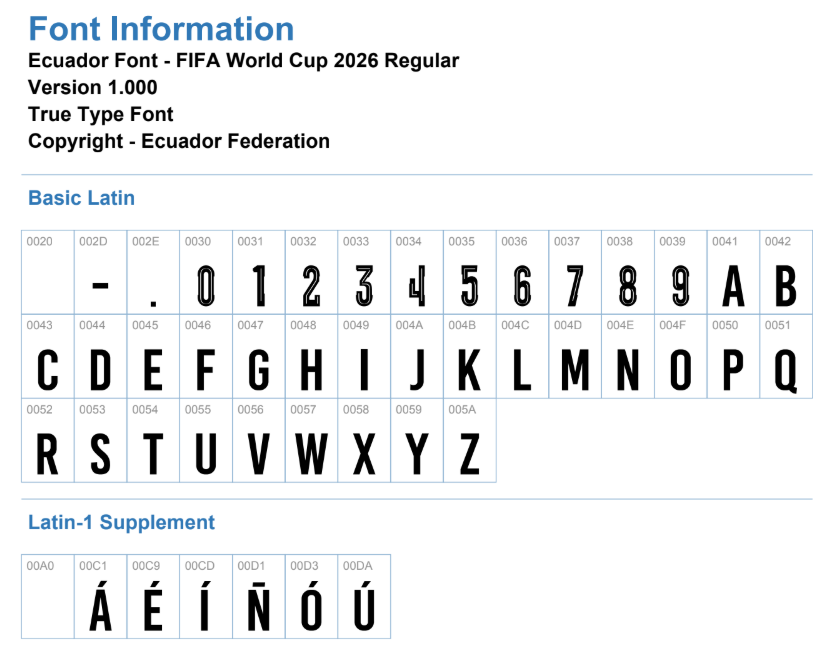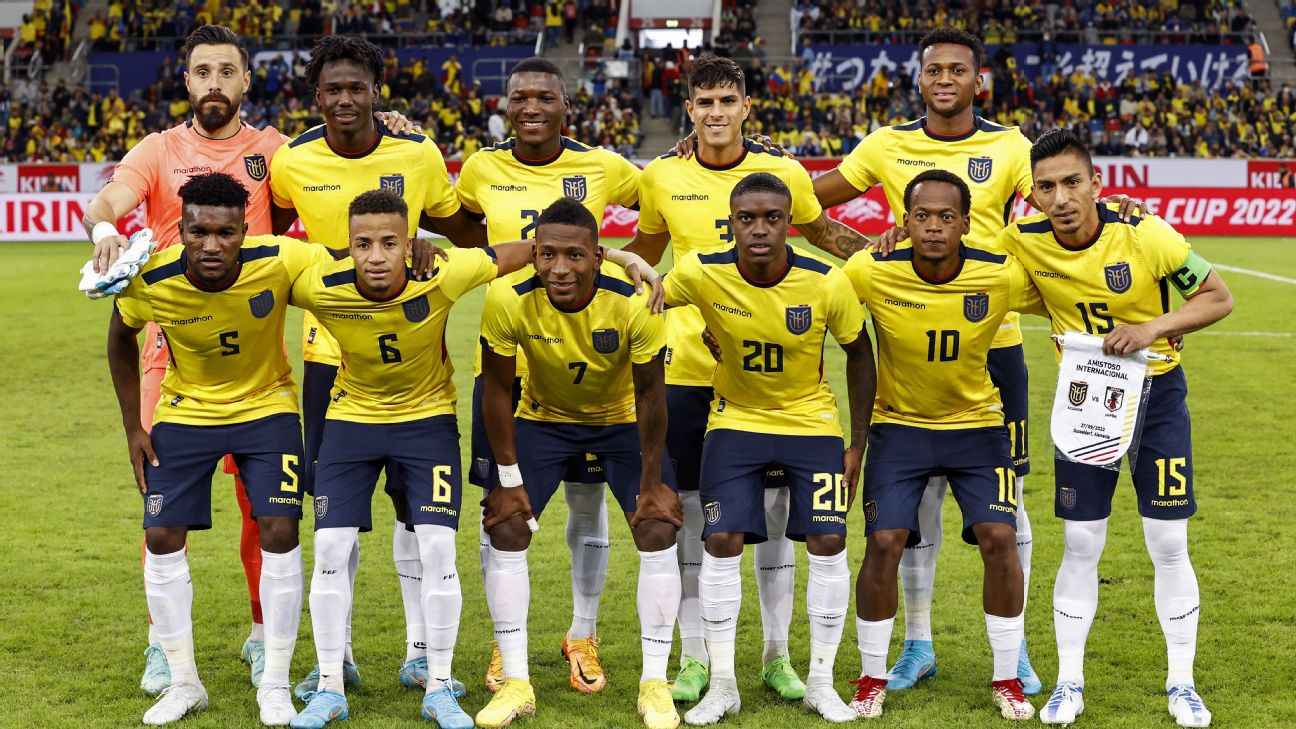
A seleção equatoriana entra em campo em 2026 com nova identidade visual que já está dando o que falar. A tipografia oficial escolhida para a temporada de Copa do Mundo traduz o momento de renovação do time comandado por nomes como Moisés Caicedo e Kendry Páez.
Mais que simples números nas costas, a fonte carrega a alma andina com um traço contemporâneo que funciona tanto no estádio quanto na tela do celular.
Estilo visual da tipografia
Os números apostam em um desenho levemente geometrizado, com ângulos que lembram os picos andinos — uma assinatura sutil que conecta a seleção à sua geografia. As curvas são limpas, sem excesso de serifa, garantindo alta legibilidade mesmo nas transmissões em movimento rápido.
A variante aplicada nos uniformes oficiais traz um contorno estratégico que destaca os dígitos sem poluir o layout da camisa. É um equilíbrio entre tradição e modernidade, com personalidade suficiente para ser reconhecida de longe pelos torcedores.
Aplicação no uniforme
No manto titular amarelo, a fonte aparece em tom azul escuro, com ótimo contraste para leitura em campo. A versão reserva, predominantemente azul, recebe os números em branco com fina camada de brilho metálico. Já o terceiro uniforme, com base grená e detalhes dourados, traz os dígitos em tom ouro envelhecido, fechando o trio com elegância.